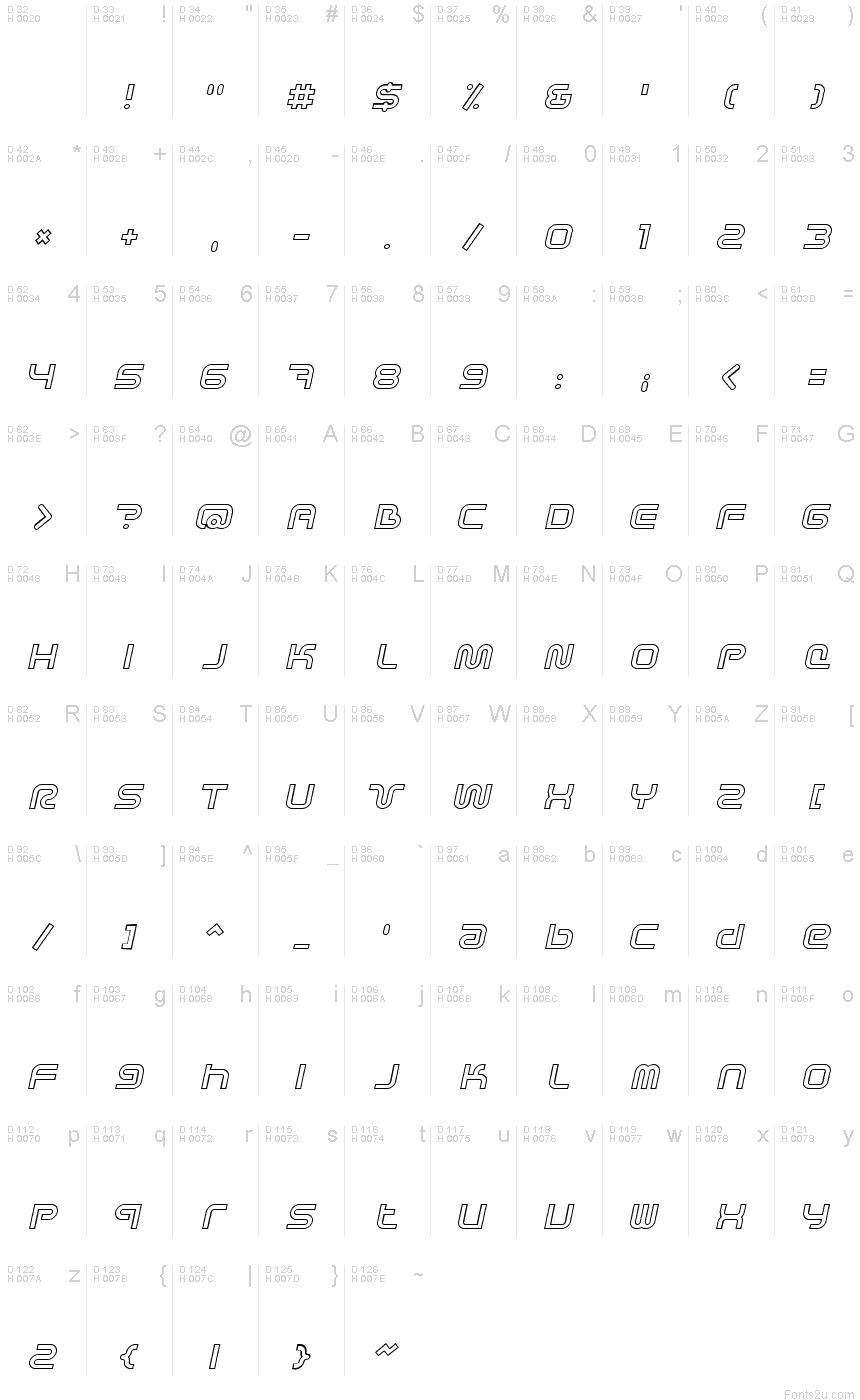
Sci Fied X Outline Italic, di dustBUST Fonts, è un font display gratuito, futuristico e contornato, che richiama il fascino del lettering sci-fi di fine XX secolo. Le maiuscole si inclinano in avanti con tratti ampi e arrotondati, mentre il doppio contorno conferisce alle lettere un aspetto vuoto e slanciato, che ricorda più la motion graphics che una tipografia statica.
Si adatta perfettamente a titoli di poster, loghi di giochi, copertine di mixtape, flyer di eventi tech e cartelli dove un font gratuito deve trasmettere un mood sintetico e dinamico. Poiché le lettere sono ampie, aperte e visibilmente inclinate, funziona bene anche per titoli brevi e monogrammi che richiedono quell'inconfondibile richiamo all'era spaziale.